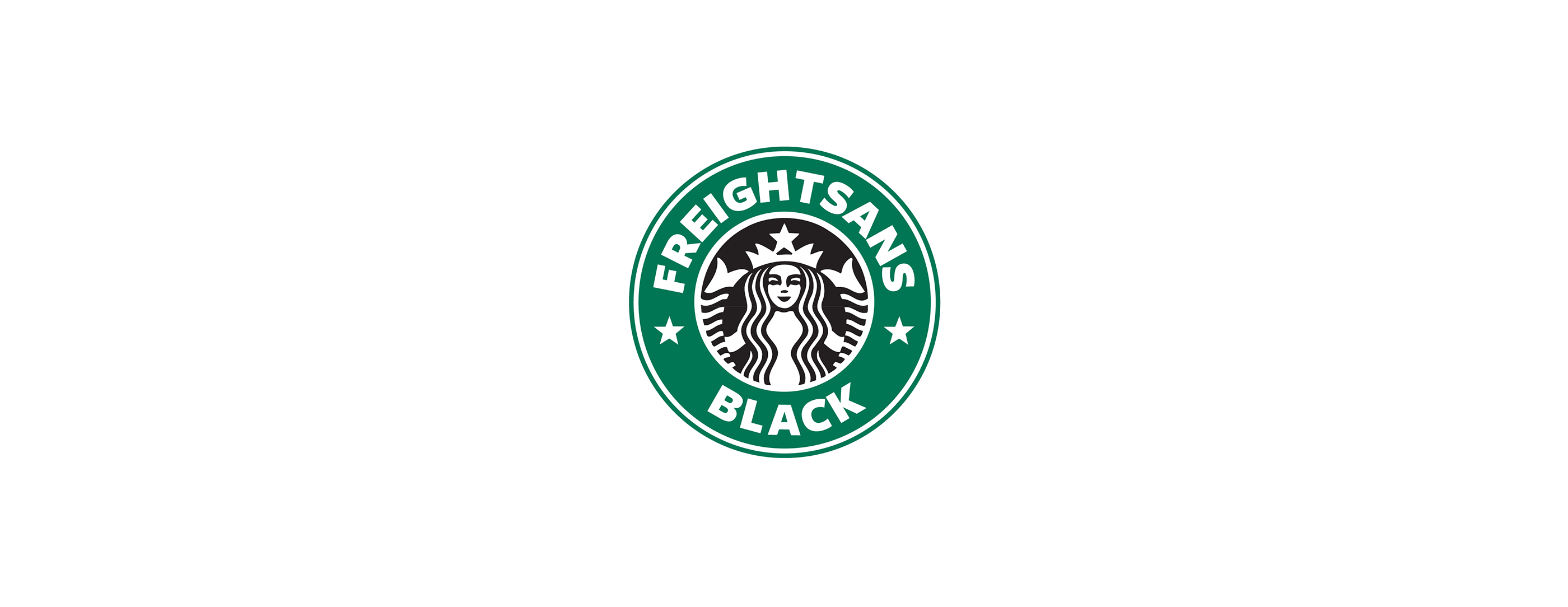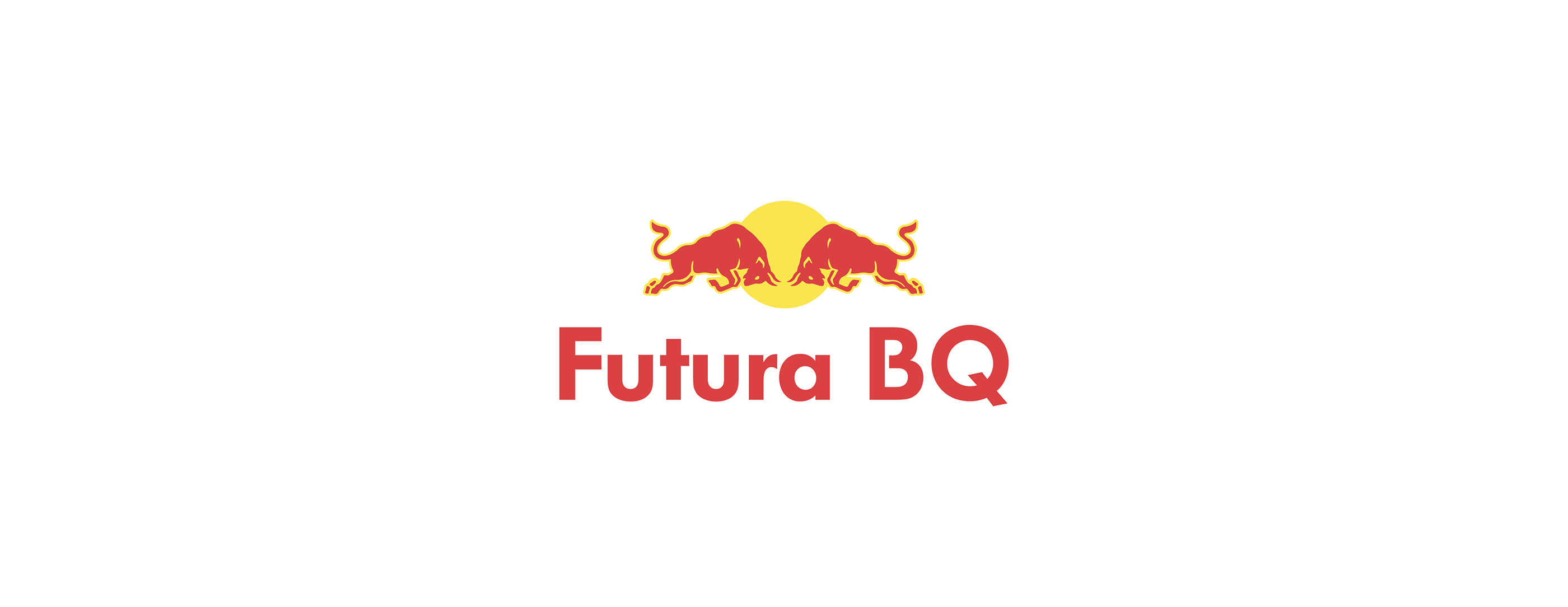
Le designer italien Emanuele Abrate a dévoilé Logofonts : un projet qui va plaire aux graphistes passionnés de typographies. Ce dernier révèle les polices utilisées par les logos des grandes marques en copiant le style graphique de ces dernières. Amusant !
On reconnaît tous en un coup d’oeil les logos des grandes marques, mais serez-vous capable de reconnaître les polices d’écriture utilisées dans ces mêmes logos ? Sans doute pas !
Et pourtant les passionnés de graphisme parmi vous connaissent l’importance de ces typographies qui sont longuement travaillées et/ou choisies pour illustrer au mieux l’ADN d’une marque et la communiquer à des millions de personnes.
Mais c’était sans compter sur l’initiative du designer italien Emanuele Abrate qui a dévoilé un projet baptisé Logofonts. Avec ce dernier, il est parti à la recherche des polices utilisées par les marques célèbres pour leur rendre hommage avec les logos des marques qui les utilisent. Les connaisseurs retrouveront ainsi tout plein de polices célèbres(Bebas Neue, Futura, Helvetica Neue, …) qui sont utilisées par des marques mondialement connues(Netflix, Nike, Whatsapp, …).